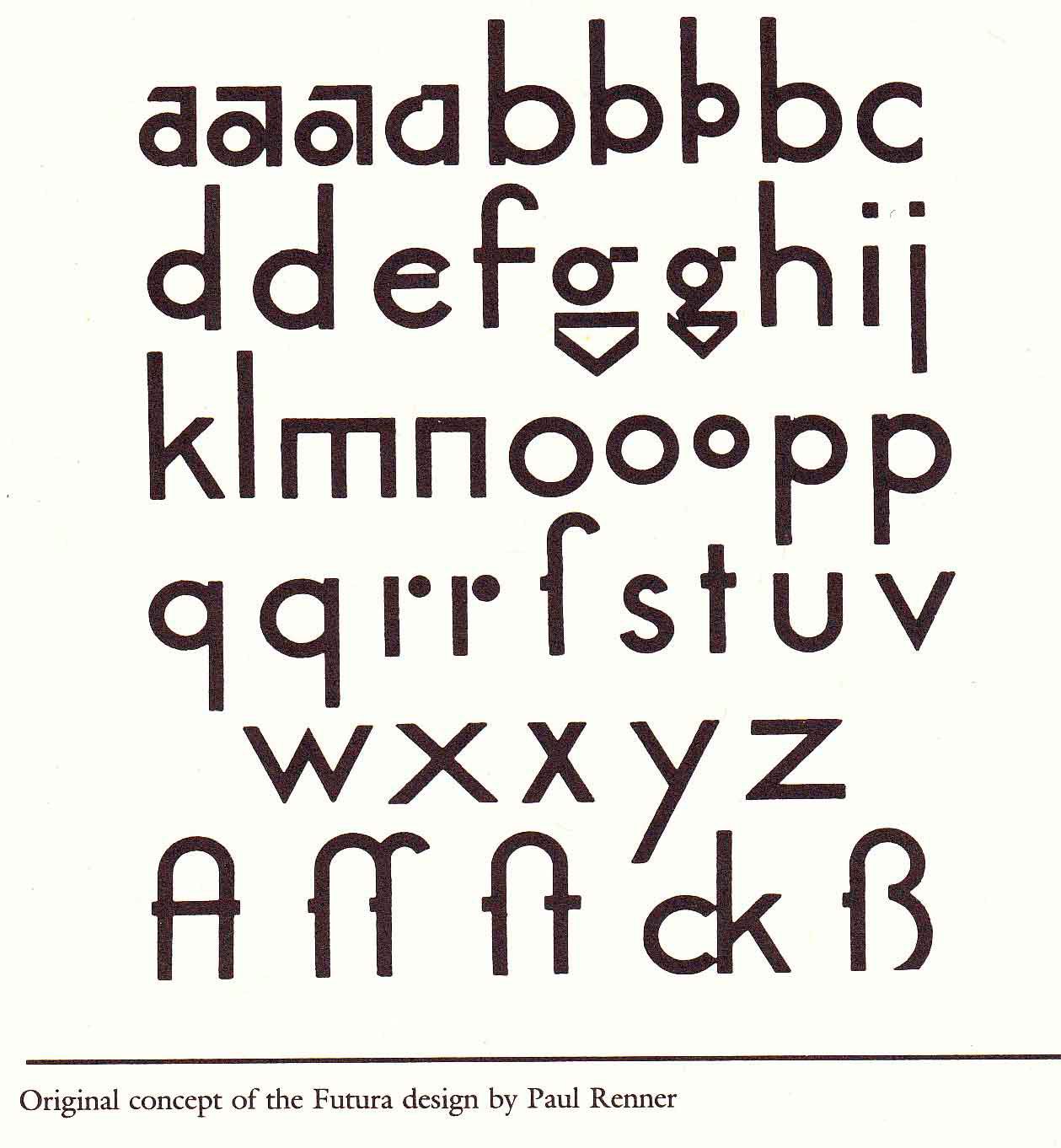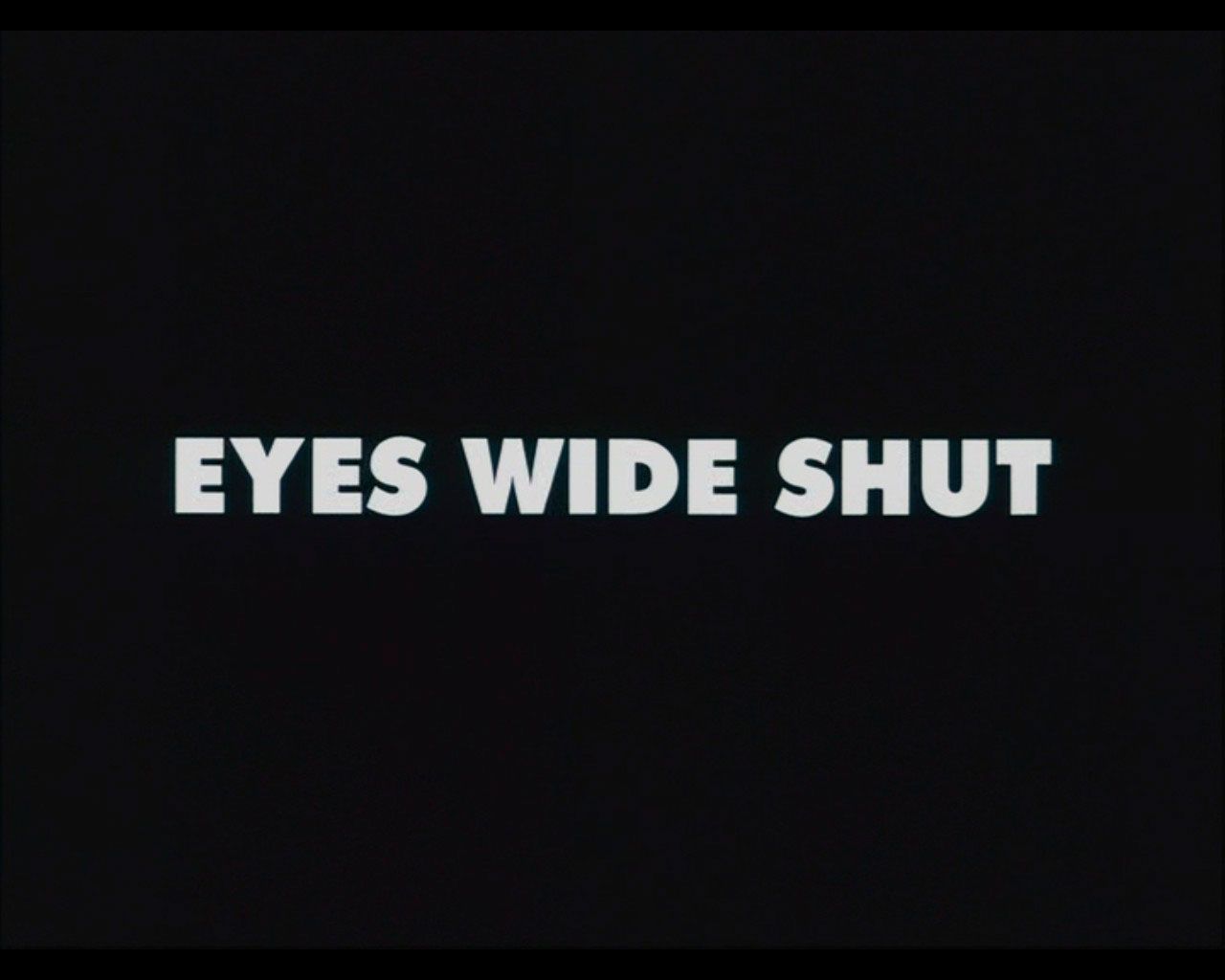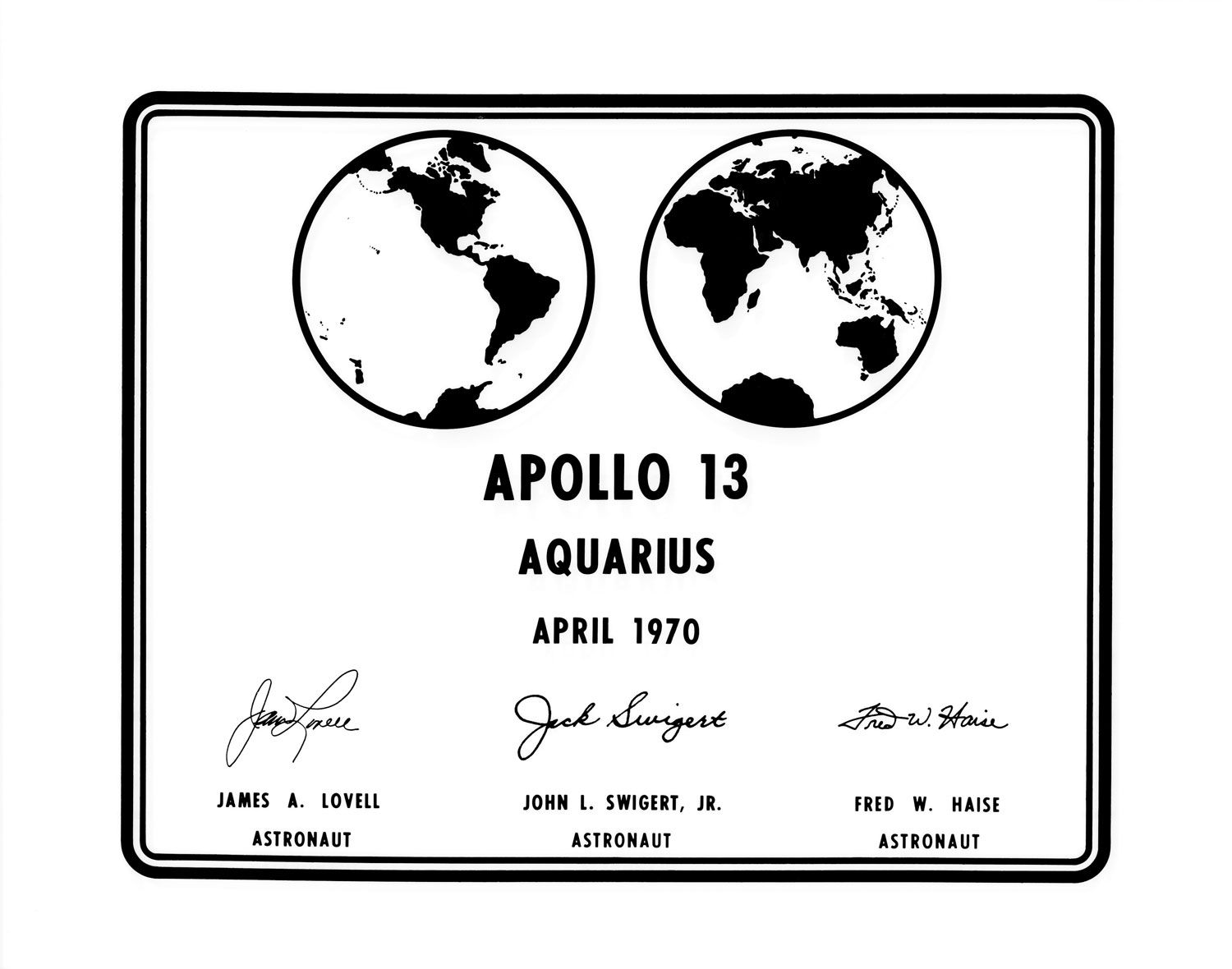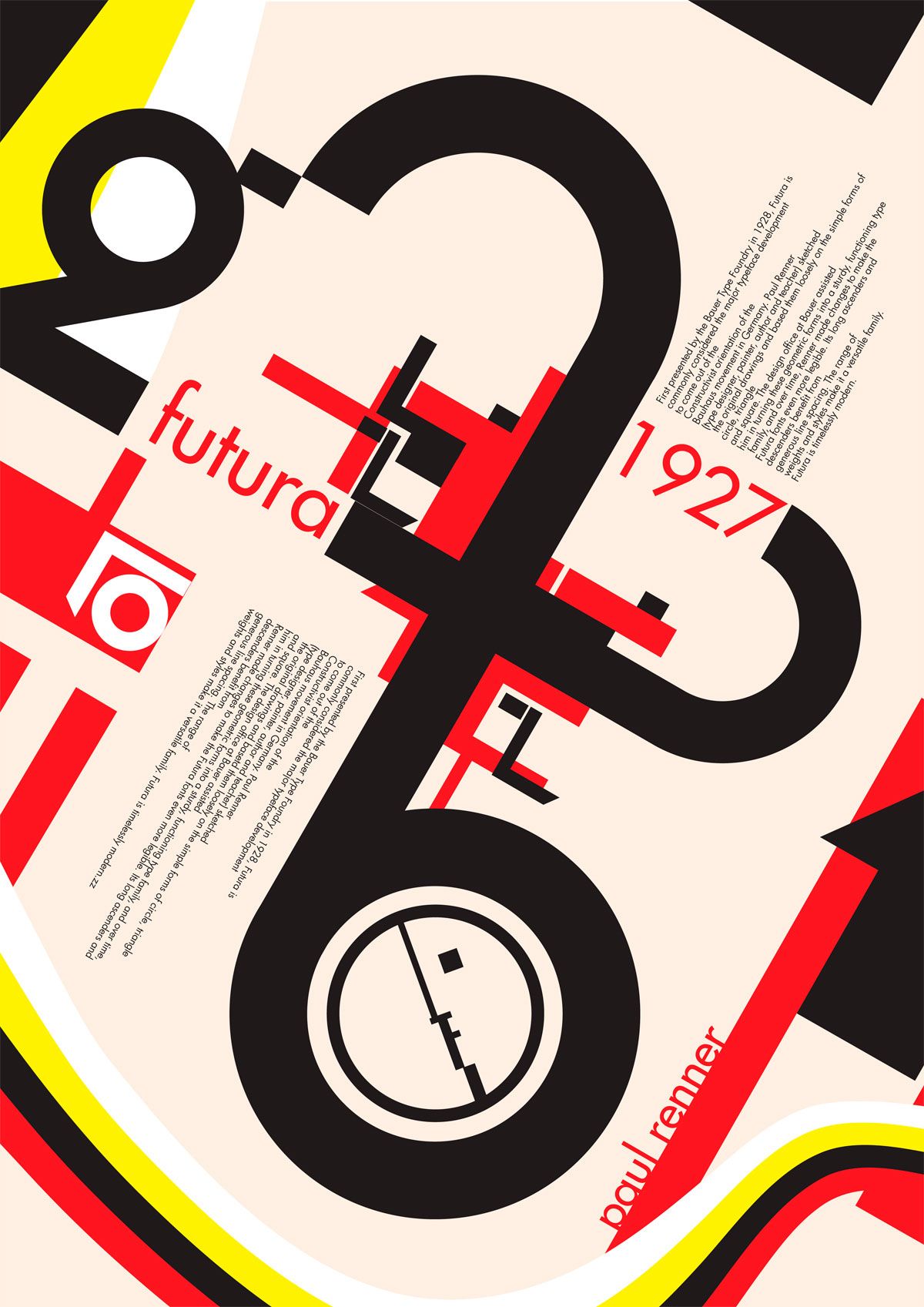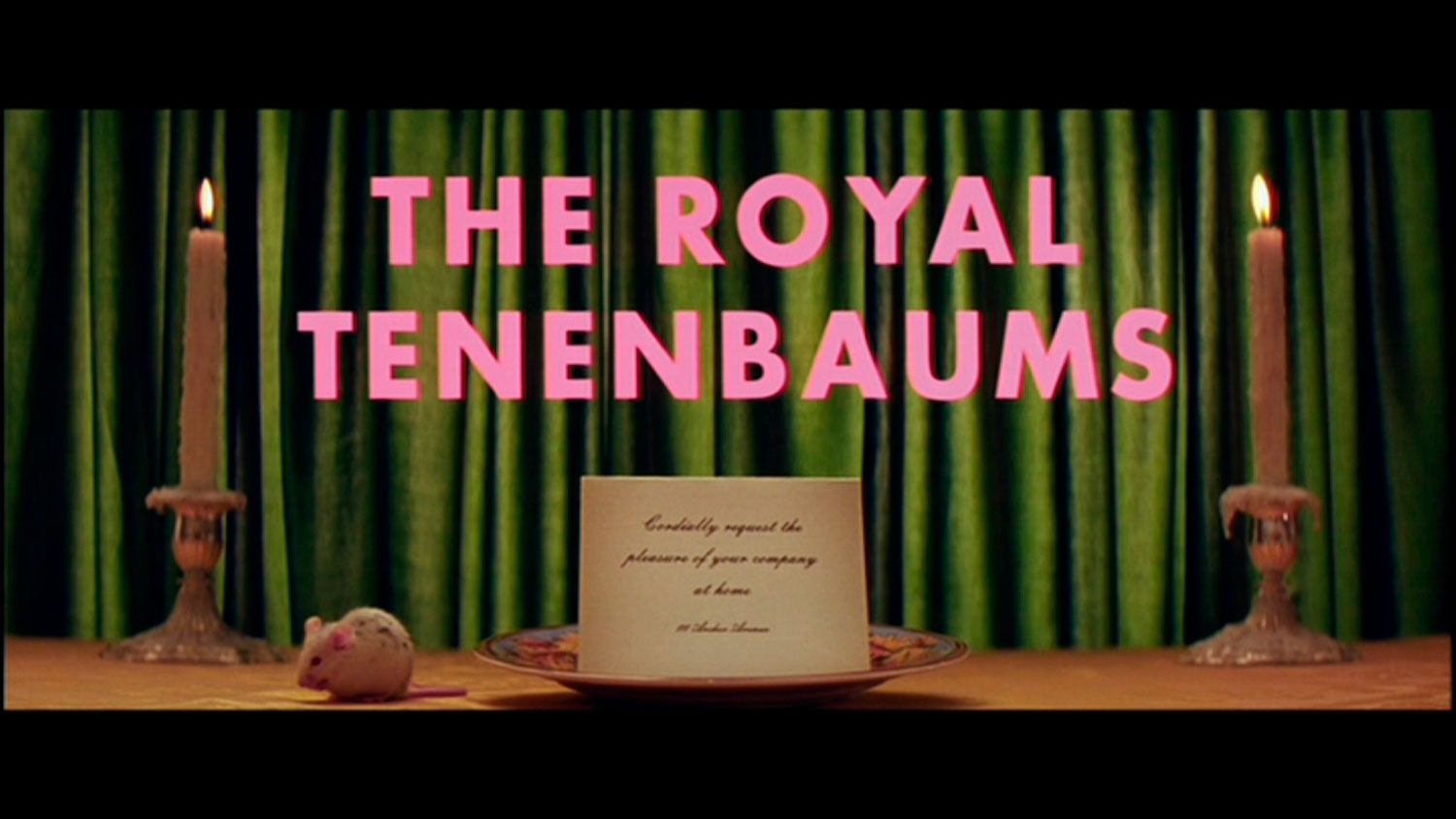
Futura: la primera tipografía de la historia en aterrizar en la luna
Este vídeo recoge, en menos de 5 minutos, la historia de cómo una tipografía escapó de los nazis y aterrizó en la luna.
La tipografía Futura, como su propio nombre indica, fue creada por Paul Renner en el año 1927, bajo la influencia de la estética de la Bauhaus, para mostrar una visión de innovación. Con la llegada de otras tipografías sans serif más modernas como Helvetica o Univers, la tipografía Futura parecía haber quedado olvidada, pero hoy en día es fácil encontrarla en todo tipo de aplicaciones. Barbara Kruger la hizo inmortal con sus diseños; directores de cine de la talla de Wes Anderson o Stanley Kubrick la han utilizado en los títulos de crédito de sus películas; IKEA, Volkswagen y Hewlett Packard, entre otros, hacen uso de ella para sus logotipos... pero el pasado de esta fuente tipográfica ha acompañado a la humanidad en otros hitos importantes en la historia.
La tipografía que los nazis venían utilizando eran tipos de letra góticos, denominados 'Fraktur', ornamentados y de aspecto antiguo. El diseño de la tipografía Futura era completamente opuesto a este, con líneas limpias y geométricas y fue catalogada como una "fuente sumamente alemana". En 1941, un decreto prohibió el uso de letra gótica por considerarla de origen judío; pero por aquel entonces Futura se había convertido en un estándar internacional y los nazis decidieron decantarse por la tipografía Antiqua.
Algunas décadas más tarde, la misma tipografía que había conseguido zafarse de las garras del nazismo fue protagonista de otro gran acontecimiento recogido en todos los libros de historia. Futura se convirtió, en el año 1969, en la primera tipografía en posarse sobre la superficie de la luna a bordo de la misión espacial tripulada Apollo 11, que transportó a Neil A. Armstrong, el primer hombre en pisar nuestro satélite.